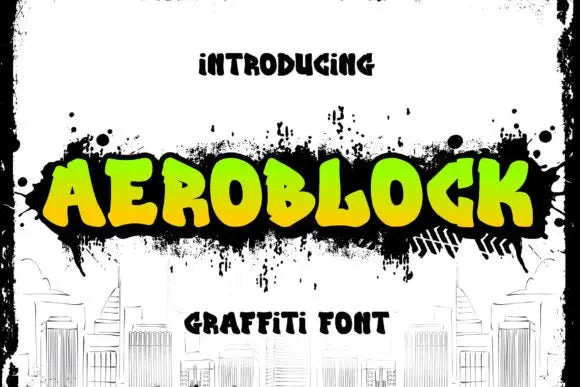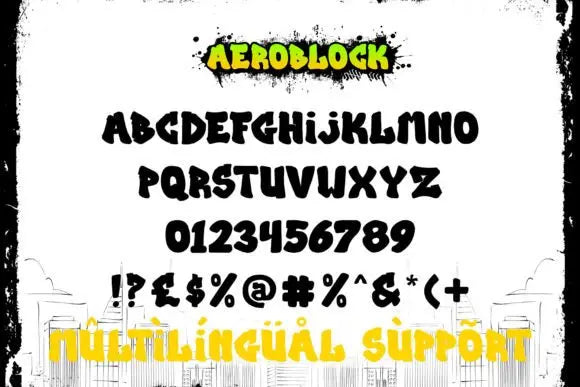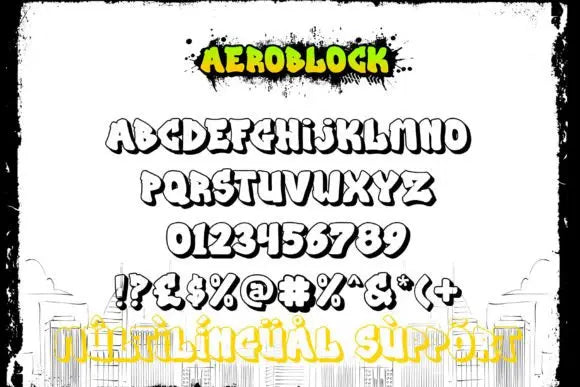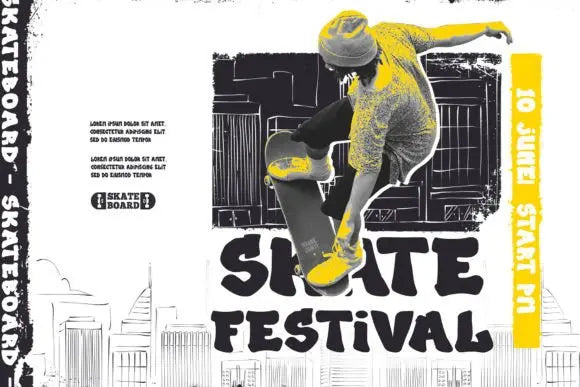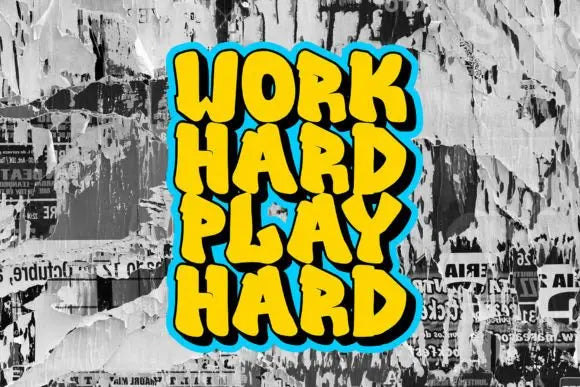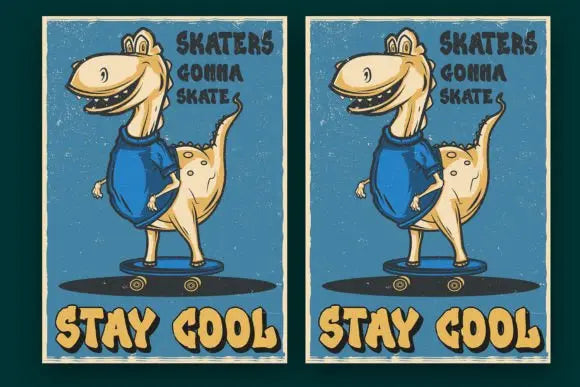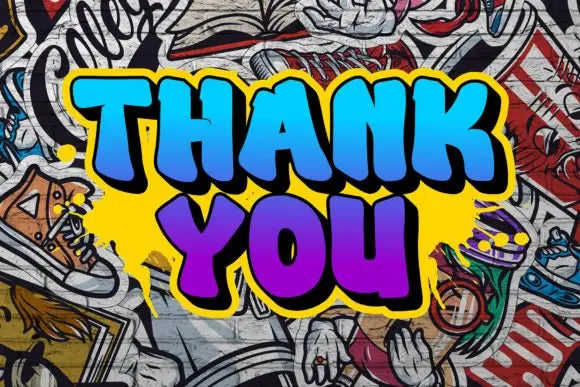
Fuente Aeroblock
Aeroblock es una fuente de graffiti urbano caracterizada por bordes redondeados y una apariencia atrevida. Ideal para carteles musicales, diseños de indumentaria, camisetas y ropa urbana, esta fuente aporta un toque vanguardista a tus proyectos.
El estilo único de “Aeroblock” lo convierte en la elección perfecta para temas de estilo callejero o graffiti urbano. Ya sea que desee crear una declaración fuerte y poderosa o simplemente agregar un toque de actitud a sus diseños, "Aeroblock" es la fuente para usted.